Trong năm 2019, xu hướng sử dụng những font chữ cực lớn, đậm và tạo cảm giác “ồn ào” sẽ tiếp tục trở nên phổ biến trong giới thiết kế. Những font chữ này chủ yếu được sử dụng như một thành tố chính, nổi bật trong thiết kế. Nếu bạn muốn người xem nhìn vào thiết kế, và hét thật to câu khẩu hiệu của bạn? Các font đậm này sẽ là lựa chọn số một dành cho bạn.
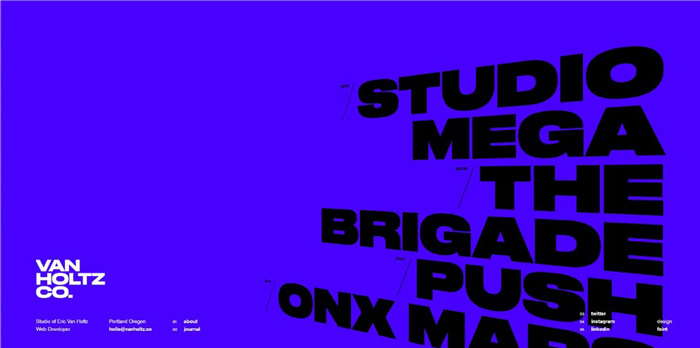
Font đậm khiến nội dung đó đập ngay vào mắt người nhìn, ở bất kỳ đâu bạn đặt vào. Poster hay từ rơi chắc chắn sẽ nổi bật từ xa, nhờ những font chữ này. Muốn Website của bạn trở nên “cá tính” hơn, thân thiện hơn? Hãy sử dụng những phông chữ lớn này.
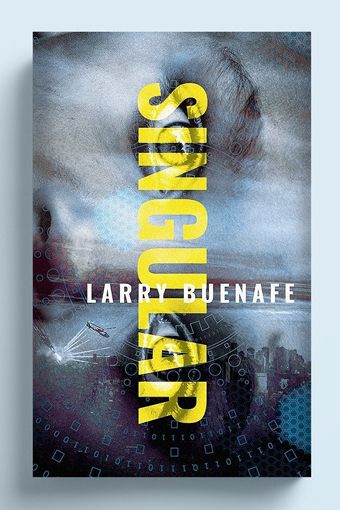
Chia tay với font chữ đậm lớn ở phần 1, chúng ta cùng chào đón font không chân tối giản, một “gã” hoàn toàn đối lập với anh bạn ồn ào nhà bên. Với xu hướng tối giản hóa trong thiết kế, font chữ Sans Serif, hay còn biết tới là font không chân chắc chắn là người bạn đồng hành không thể thiếu cho những nhà thiết kế theo trường phái tôn thờ sự đơn giản.
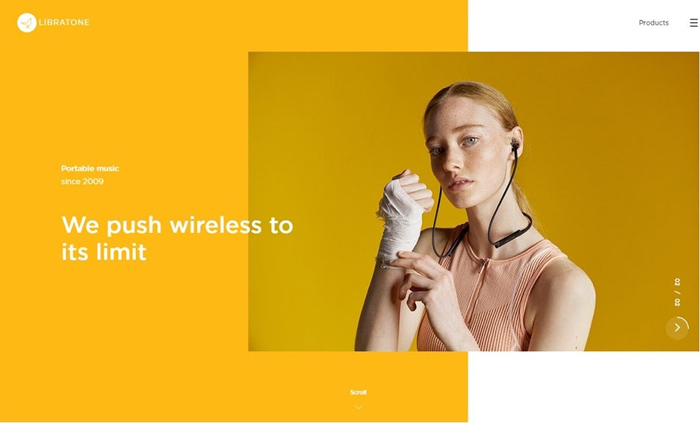
Nhờ vào sự tối giản, những phông chữ này có thể dễ dàng thích ứng với nhiều trường hợp khác nhau. Nó cũng không yêu cầu quá nhiều yếu tố trực quan. Khi được sử dụng một cách hợp lý, các font chữ này chắc chắn sẽ đem lại hiệu quả vô cùng lớn.
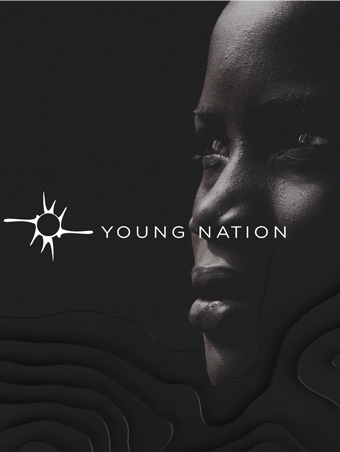
Những phông không chân tối giản khơi gợi cho người đọc cảm xúc nhẹ nhàng, thư thả, trầm lắng mà cũng vô cùng điềm tĩnh. Thay vì phải hét lên với câu khẩu hiệu lớn, bạn hãy cho người xem “một chút bình yên, một chút sâu lắng”. Hãy để không gian lắng đọng cùng những font chữ này.
Càng hướng về tương lai, con người ta lại có xu hướng nuối tiếc, hoài niệm những ký ức đã qua. Trend vintage đang thống trị trong thế giới thiết kế, từ thời trang, nội thất đến thiết kế đồ họa. Sẽ chẳng ngạc nhiên gì khi trong năm 2019, chúng ta đón nhận rất nhiều những font chữ được thiết kế ra để bắt kịp trào lưu Vintage này.
Bạn có thể sử dụng những font chữ vintage này để tạo logo hay cho các sản phẩm bao bì, những thứ đòi hỏi sự trang nhã và lịch sự, nghiêm túc. Bạn còn có thể sử dụng các font chữ đậm, mang hơi hướng phức tạp mà hoài cổ. Với những ai muốn níu giữ một chút kỷ niệm trong một thế giới hiện đại bộn bề, phong cách vintage chắc chắn sinh ra là để dành cho bạn.
Các font chữ mang hơi hướng viết tay chưa bao giờ tỏ ra hết thời. Nó là sự tổng hòa giữa tính lưu loát của nét chữ viết tay, với sự trang nhã, thanh lịch của những ký tự thư pháp.
Trong năm 2019, các phông viết tay (dạng script) đã phát triển và biến hóa rất nhiều với đa dạng những hình thù, phong cách khác nhau. Chúng có thể tinh nghịch, cổ điển, hay nghiêm túc, đơn giản hoặc phức tạp. Với font chữ viết tay, bất kỳ kiểu dáng nào cũng có. Bạn sẽ phải choáng ngợp trước những gì phông chữ này mang lại đến sản phẩm của mình.
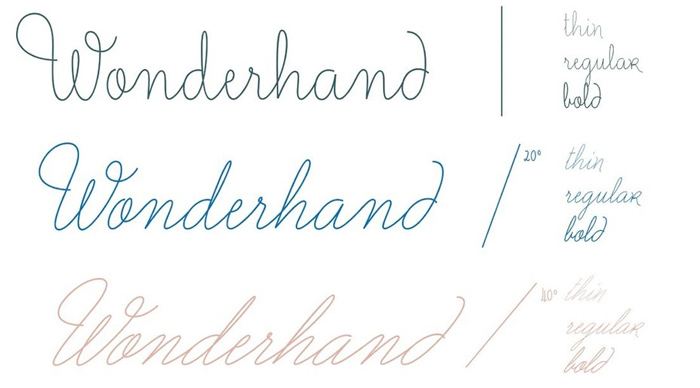
Một khi bạn đang bí ý tưởng về font chữ tiêu đề, hay muốn tìm kiếm một phông chữ thể hiện sự trưởng thành và sang trọng, các outline font (phông chữ viền, có hình bao) là lựa chọn dành cho bạn.
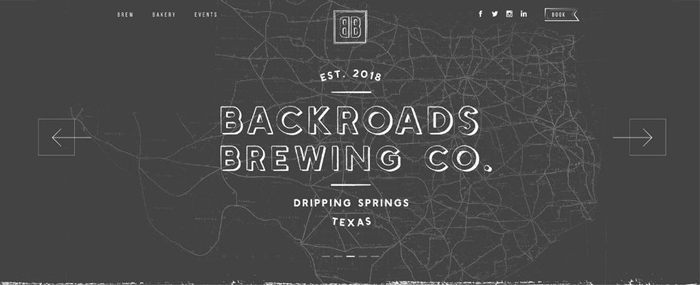
Năm 2019 tới, font chữ này “xâm lấn” khắp mọi nơi, trong mọi sản phẩm thiết kế. Tính hiện đại, nghiêm túc khiến font chữ này được dùng để diễn đạt sự trưởng thành và thành đạt. Có rất nhiều kiểu cách được thiết kế cho font chữ outline này, từ lớn tới nhỏ, đậm tới nhạt, nghiêng, handmade, sharp, và nhiều hơn nữa.
Có một font chữ, mà nó là sự kết hợp của sự nổi bật, thu hút mọi ánh nhìn, với tính trang nhã, lịch thiệp. Đó chính là những phông có chân có độ tương phản cao (high-contrast serif font). Trong năm 2019, nó thực sự là một cơn sốt và có mặt ở khắp mọi nơi.
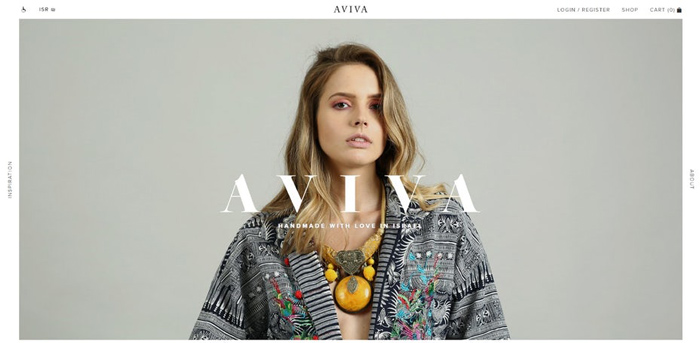
Sự tương phản ở đây đến từ khía cạnh về chiều rộng: Một phần các ký tự có xu hướng mỏng hơn so với phần còn lại. Hai phần có sự tương phản cực lớn, tạo sự khác biệt rõ nét, đồng thời làm nổi bật lẫn nhau.
Chính sự tương phản này tạo nên những thiết kế chữ cực đậm, mà sang trọng. Sử dụng phong cách typography này, bản thiết kế của bạn sẽ được nâng lên một tầm cao mới.
Một thiết kế mang đầy nét tinh nghịch và đáng yêu trong năm 2019, đó chính là những quirky fonts (thường là những font được thiết kế không theo nhiều khuôn mẫu, mang tính ngẫu hứng và thể hiện tính tươi vui, tinh nghịch). Chúng vừa có nét “vụng về”, lại vô cùng đáng yêu và dễ mến. Quirky font mang tới cho người xem cảm giác bất ngờ, vui vẻ bởi sự thoải mái và tự nhiên mà nó đem lại.
Xu hướng font chữ Quirky thích hợp với những nội dung nhẹ nhàng, hài hước, mang ý nghĩa khích lệ, đủ để làm người xem nở 1 nụ cười trên môi. Những ấn phẩm thiết kế sử dụng Quirky font thường đem lại cho người xem một trải nghiệm tươi mới và lạc quan.
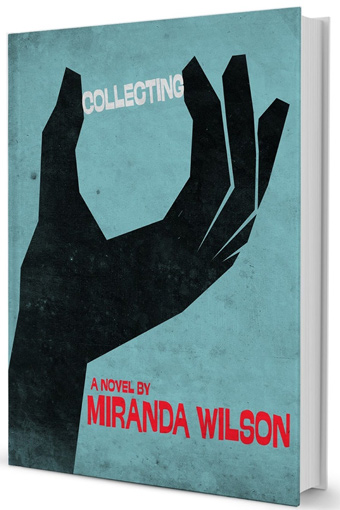
Xu hướng font chữ Messy (Những font mang tính lộn xộn, xù xì có thể coi là “trai hư” trong họ nhà Typography) là một trường hợp đặc biệt trong Typography. Vậy mà đến năm 2019, nó lại trở thành xu hướng được vạn người mê. Vẻ đẹp của nó thật đặc biệt: Đó là sự phá cách, bỏ mọi quy tắc về cái đẹp mà bạn từng biết.
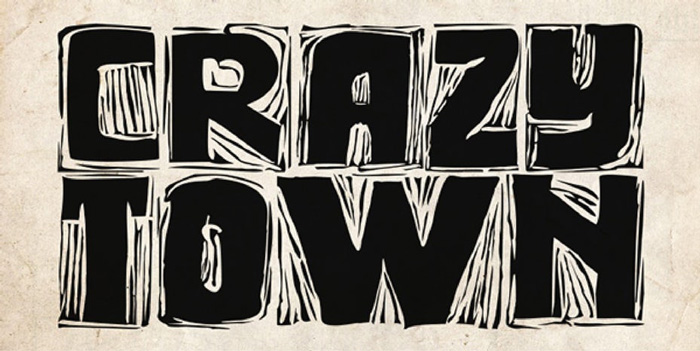
Nhưng không phải những gì bạn không thích thì cả quả đất này cũng chối từ. Luôn có một mạch nước ngầm bên cạnh mạch nước chính. Nếu bạn muốn một sản phẩm có thể bứt phá khỏi khuôn khổ, tìm kiếm cho mình một cá tính riêng độc nhất, đây là thứ dành cho bạn.